白洲毛筆太楷書体
力強くダイナミックなストローク構成が特徴のこの書体は、看板やポスター、サムネイルのデザインに効果的です。
この書体ファミリーの各フォントに含まれる英数字、ひらがな、カタカナは、それぞれ独自の文字幅を持つプロポーショナル字形としてデザインされています。
白洲毛筆極太楷書体
力強く肉太な筆致が魅力のこの書体は、看板やポスターなど、印象的に見せたいデザインに最適です。
各フォントに含まれる英数字・ひらがな・カタカナは、それぞれの字形に合わせたプロポーショナル設計となっています。
白洲ペン楷書体
この書体は、字形の調和に細心の注意が払われ、機械的な処理を避けて手書きでストロークが描かれています。手書き学習のお手本となる美しい文字セットです。
この書体ファミリーの各フォントに含まれる英数字、ひらがな、カタカナは、それぞれ独自の文字幅を持つプロポーショナル字形としてデザインされています。
白洲学校ペン楷書体
文部科学省の学習指導要領に基づいてデザインされた、手書き文字に近い書体です。「はね」、「とめ」、「はらい」などの字画も、学習指導要領に準拠してデザインされています。
この書体ファミリーの各フォントの英数字、平仮名、片仮名は、それぞれ独自の幅を持つプロポーショナルグリフとしてデザインされています。
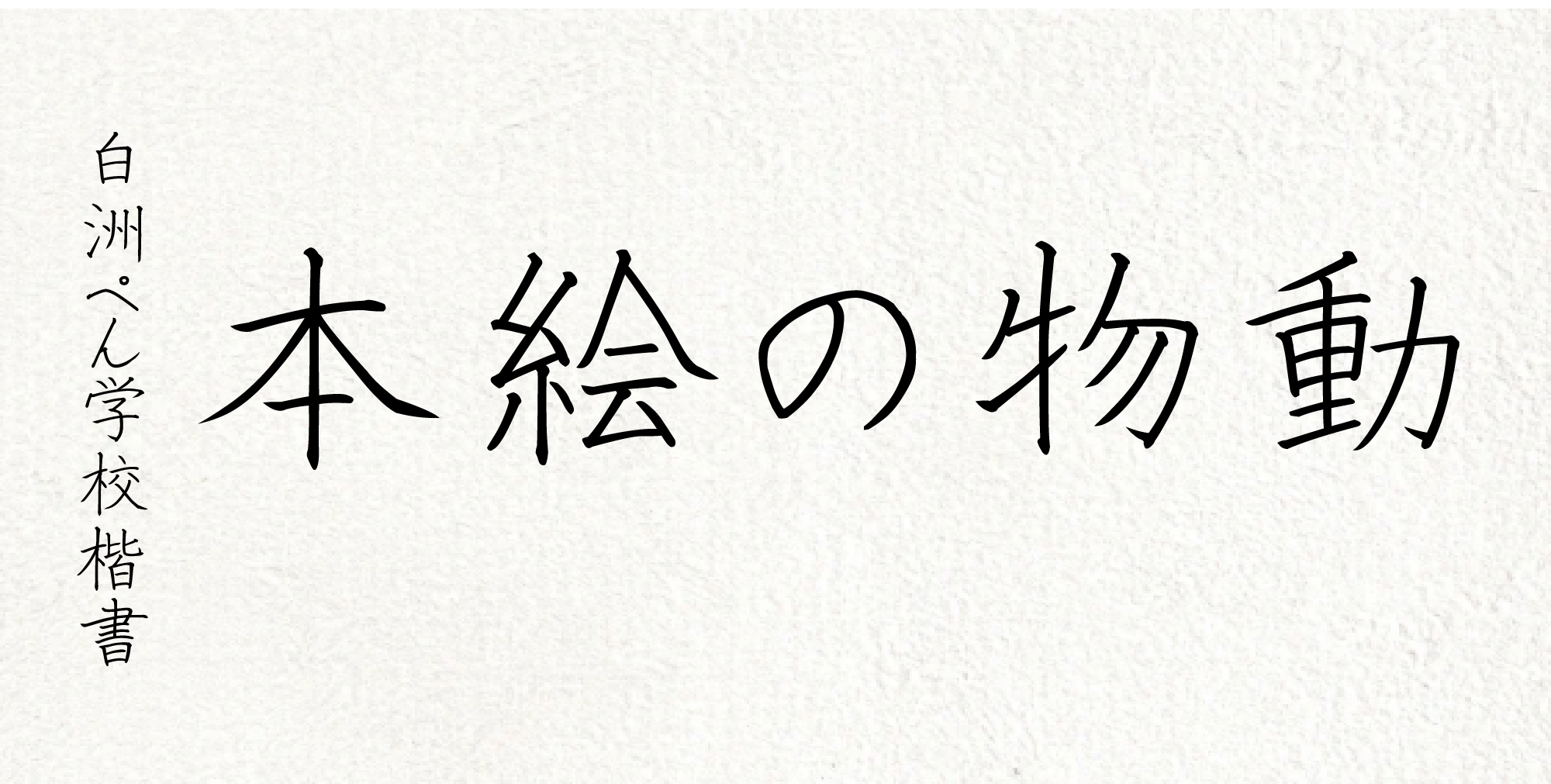
| 白洲毛筆太楷書体 | W1 / W3 / W6 |
| 白洲毛筆極太楷書体 | W1 / W3 / W6 |
| 白洲ペン楷書体 | W1 / W3 / W6 / W9 / W12 |
| 白洲学校ペン楷書体 | W1 / W3 / W6 / W9 / W12 |